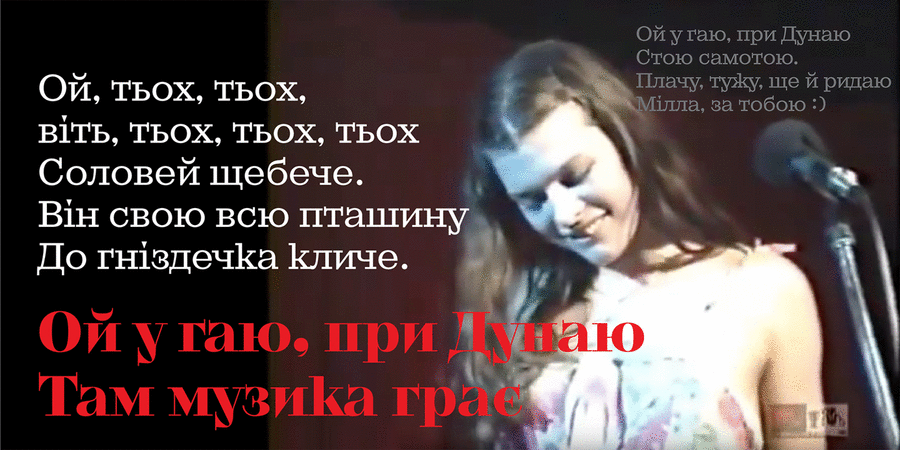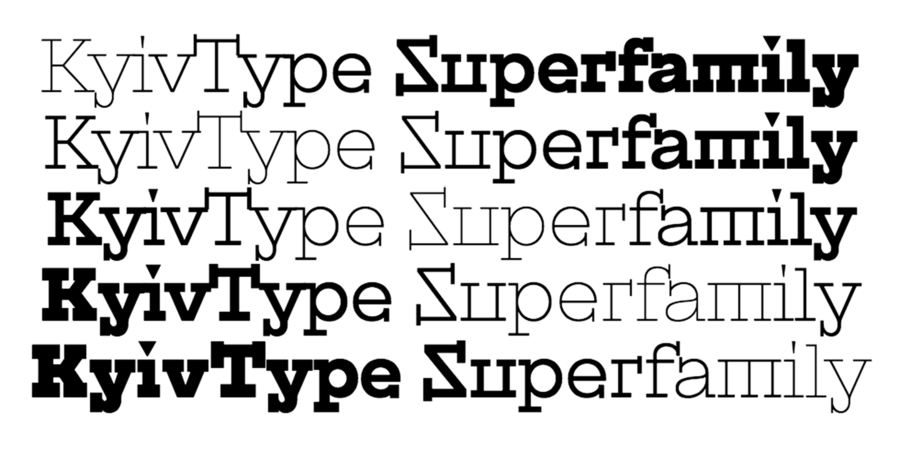
Карбована частина супергарнітури для Києва. Шрифт для Києва з багатьма обличчями та крутим характером з'явився тоді, коли до проекту #newkyivlogo (каштановий лист як логотип Києва) приєднався Дмитро Растворцев. «Київ різний. Трохи брутальний. Трохи інтелігентний. Трохи тусовочний. Трохи хіпстерський. Трохи традиційний. Це еклектичне місто. Воно легко включає різне та різних – це створює той Київ, який я люблю. Шрифт такий самий – трохи брутальний, трохи інтелігентний, трохи тусовочний, трохи традиційний, трохи дикий. І дуже-дуже різний.» – так описує проект Олександр Трегуб – засновник Projector та ідейний натхненник нового логотипу Києва.
Асоціації з сімейством шрифтів Kyiv Type SerifОсобистість і характер гарнітури:
міцний, надійний, серйозний, цікавий, якісний, міський, культурний, виразний, впевнений, прямокутний, залізний, сталевий, сильний, індустріальний, техногенний, мотивуючий, суворий, гучний, крутий, урбаністичний, відповідальний, креслярський, інженерний, амбітний, сексуальний, робочий, іронічний, стійкий, вінтажний, рівний, гострий, твердий, оригінальний, характерний, модний, химерний, різкий, претензійний, екстравагантний, нонконформістський, богемний, точний, переконливий, стабільний, чіткий, статичний, консервативний, традиційний, майстерний, старомодний, ностальгічний, добротний, олдскульний
Місто, дизайн, промисловість, техніка, верстат, інструмент, прилад, електростанція, енергетика, завод, тренажери, архітектура, наука, ремонт, блокбастер, бойовик, екшен, поліція, захист, охорона, сталевар, мотор, двигун, будівництво, будматеріали, математика, хімія, урбаністика, конструктор, фінанси, медицина, креслення, інженер, робочий, нафта, селфі Гарнітура має ознаки стилів: